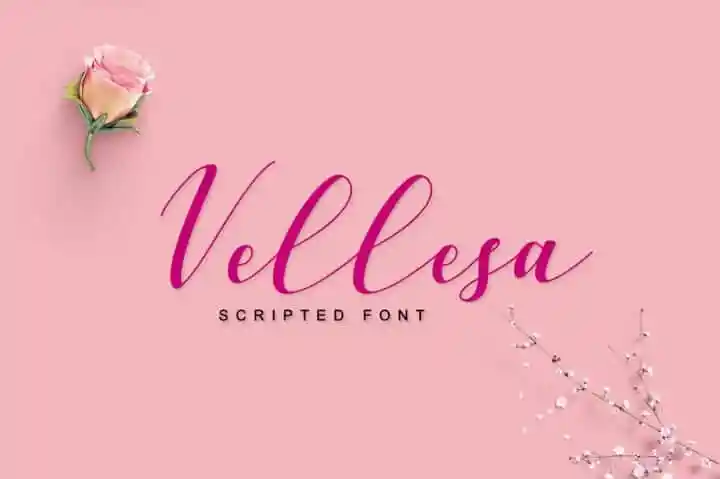
Vellesa Script Font – Download Grátis
A Fonte Vellesa Script é uma delícia para designers que buscam algo elegante e moderno. Ela combina a versão moderna e fresca de um estilo tipográfico com detalhes adoráveis de escrita manual, caracteres decorativos e uma linha de fundo dançante, tudo combinado num único pacote. Esta fonte é tão atraente que pode ser usada em diversas maneiras, desde cartões de convite até materiais de marca, cartões de visita, citações ou panfletos. Seu estilo chamativo torna-se particularmente brilhante quando aplicado em design de cartão de aniversário ou em uma publicidade ambiciosa. É a escolha perfeita para quem deseja criar algo elegante e pessoal, sem perder aquela modernidade tão valorizada atualmente.
Designer: Pointlab Studio